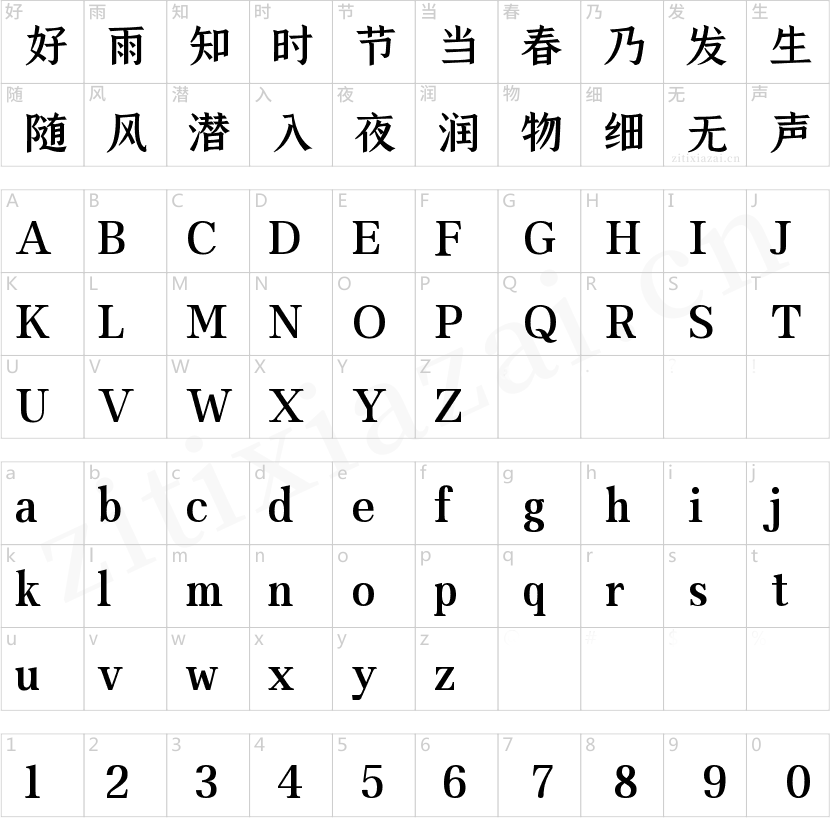
字魂手刻宋
字魂手刻宋,这款字体结构工整、笔画清晰,兼顾美观与易读性,适用于标题、正文、海报、包装、LOGO 等多种场景。字形优雅稳定,风格百搭耐看,适配日常排版与创意设计,让文字呈现更舒适、更具质感。字魂手刻宋一笔一画,皆是细节,以均衡的比例、流畅的线条打造舒适视觉体验,字形端正大气,风格简约现代。无论是商业设计、品牌宣传还是日常排版,都能轻松驾驭,让文字更有格调与力量。字魂手刻宋字体下载。